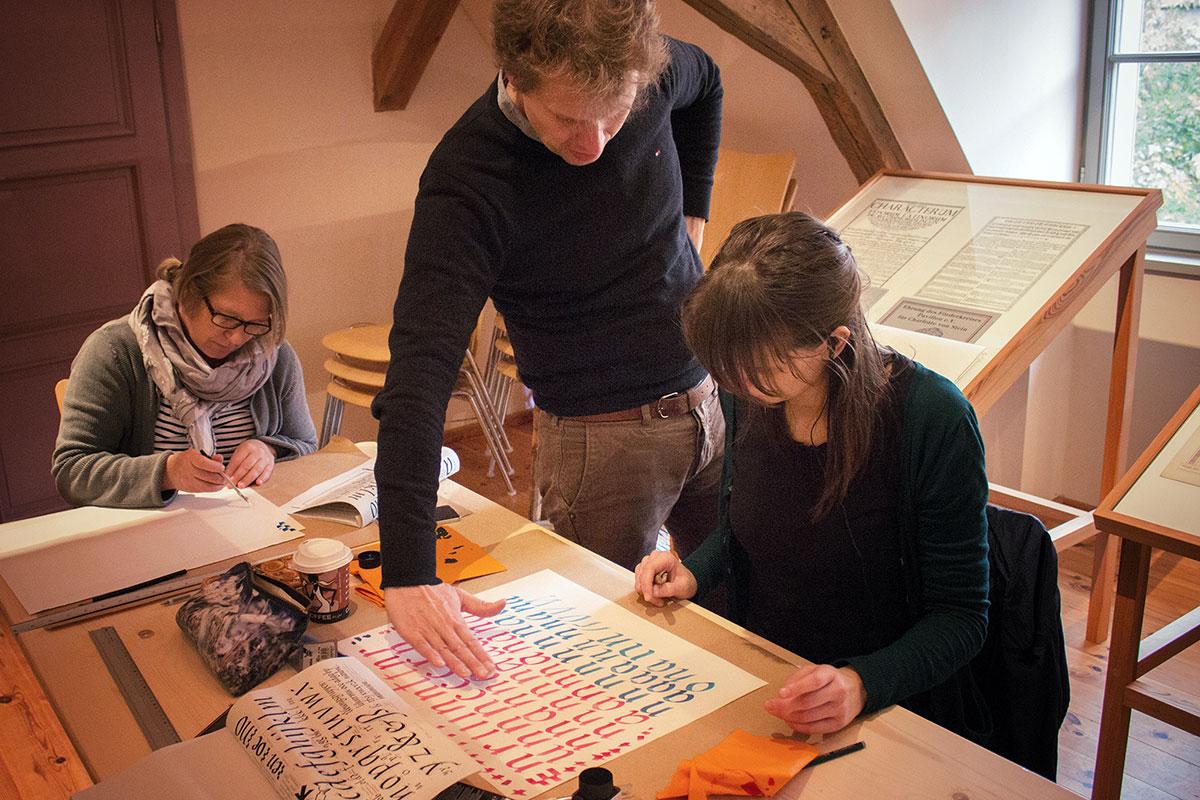
Script-Expeditionen: Von Kalligrafie zu Handlettering
Ohne Wurzeln keine Flügel. Dieser dreiteilige Kalligrafie-Kurs mit Tobias-David Albert baut von sich von einer Renaissance-Kursiven oder Italic über das Schreiben von englischer Schreibschrift bis hin zu amerikanischen Brushscript-Schriften auf. Alle drei Kurse sind so angelegt, dass sie auch ohne die Teilnahme an den anderen beiden möglich sind. Die Anmeldephase für den dritten Teil ist jetzt eröffnet.
Der dritte Teil baut auf Kursiv und Spitzfederanglaise auf. Hier geht es vor allem um die Werkzeuge Spitzpinsel und Breitpinsel. Großes und kleines Schreiben wird nach guten Vorlagen geübt. Wegweisende Bücher werden vorgestellt und mit alten und modernen Werkzeugen geübt. Hier nähern wir uns eher den jüngeren amerikanischen Schreibtraditionen im kommerziellen Lettering und spannen aber gleichzeitig einen Bogen zu den Breitpinsel Beschriftungen der späten Antike.